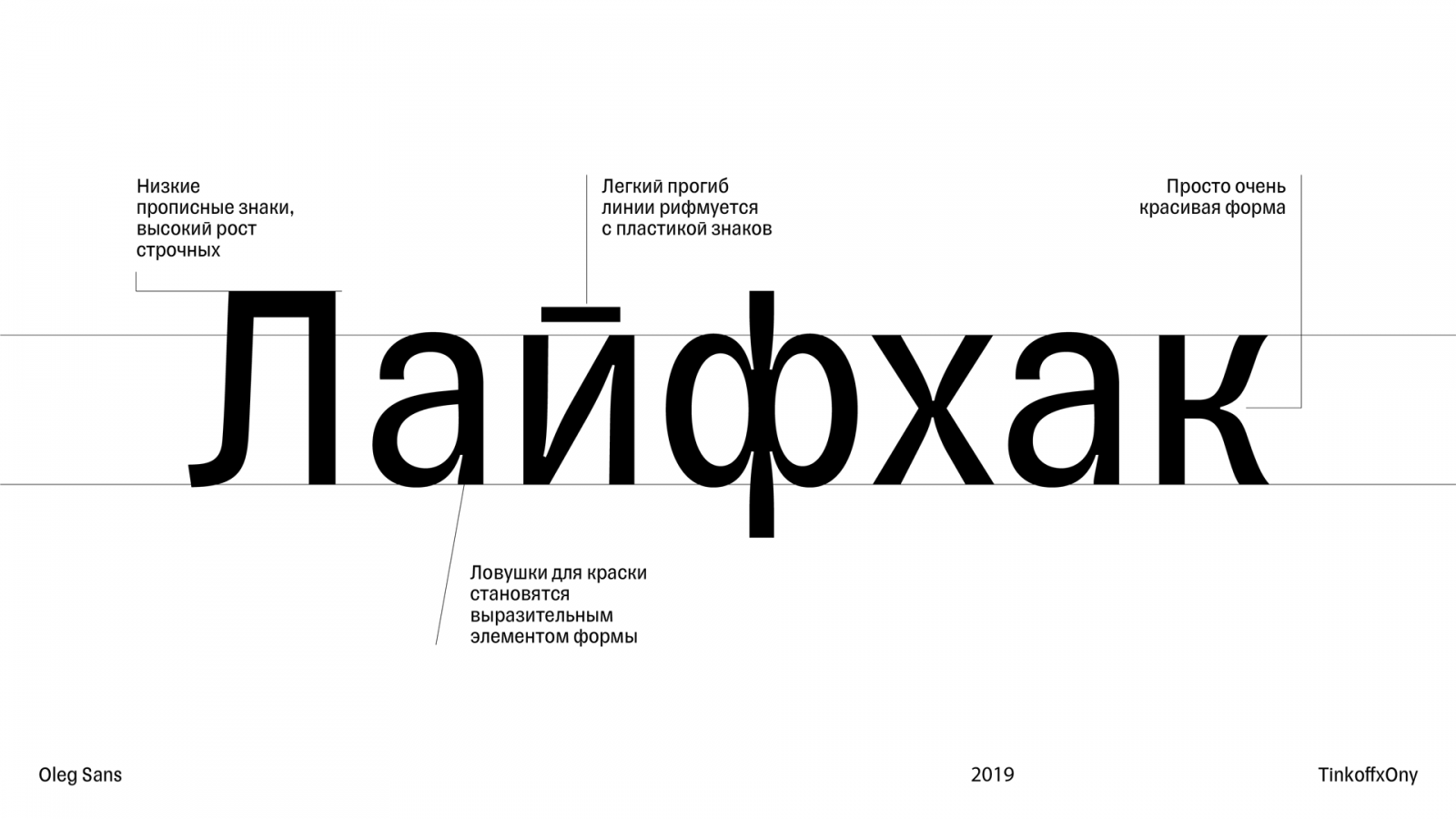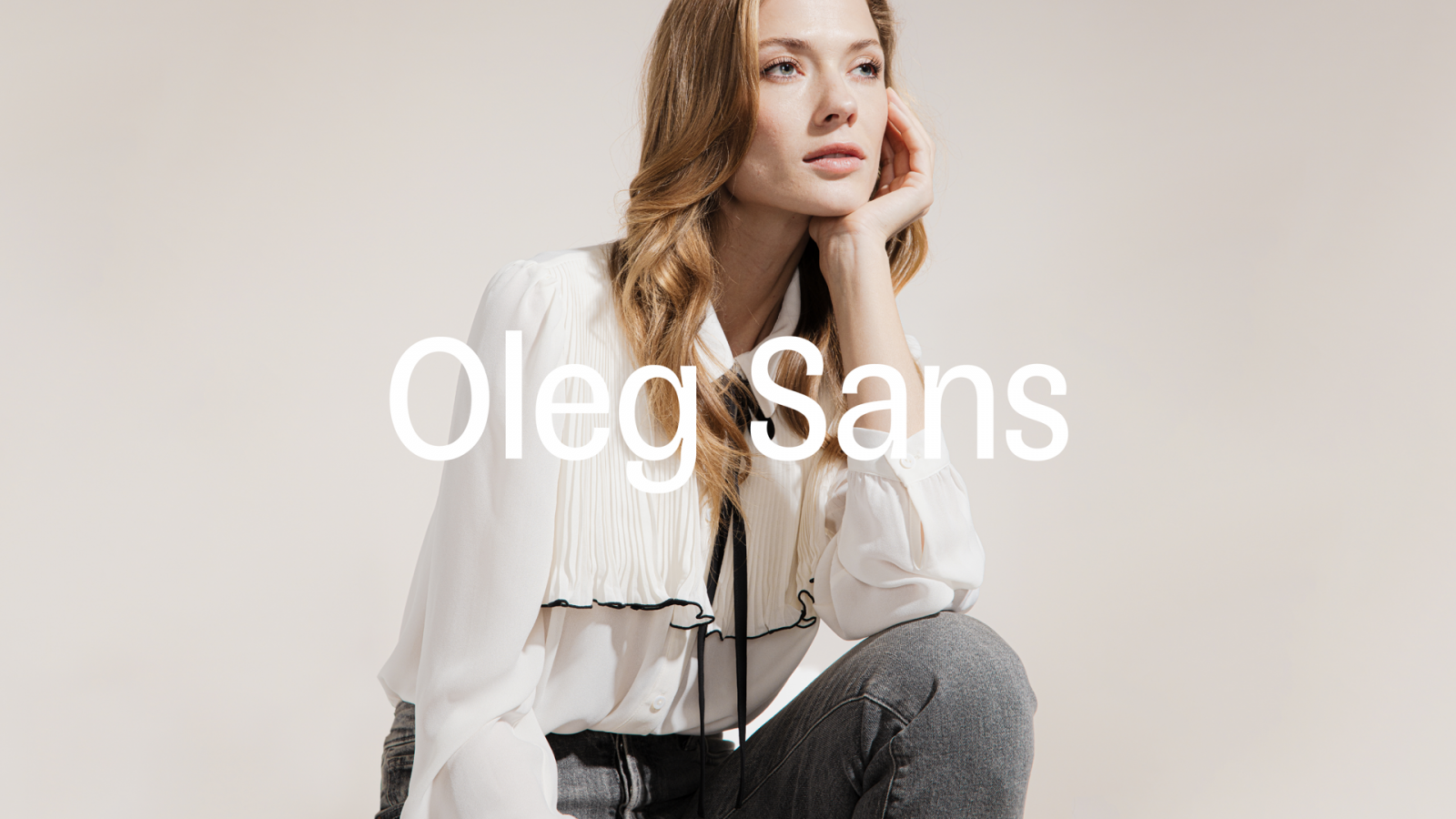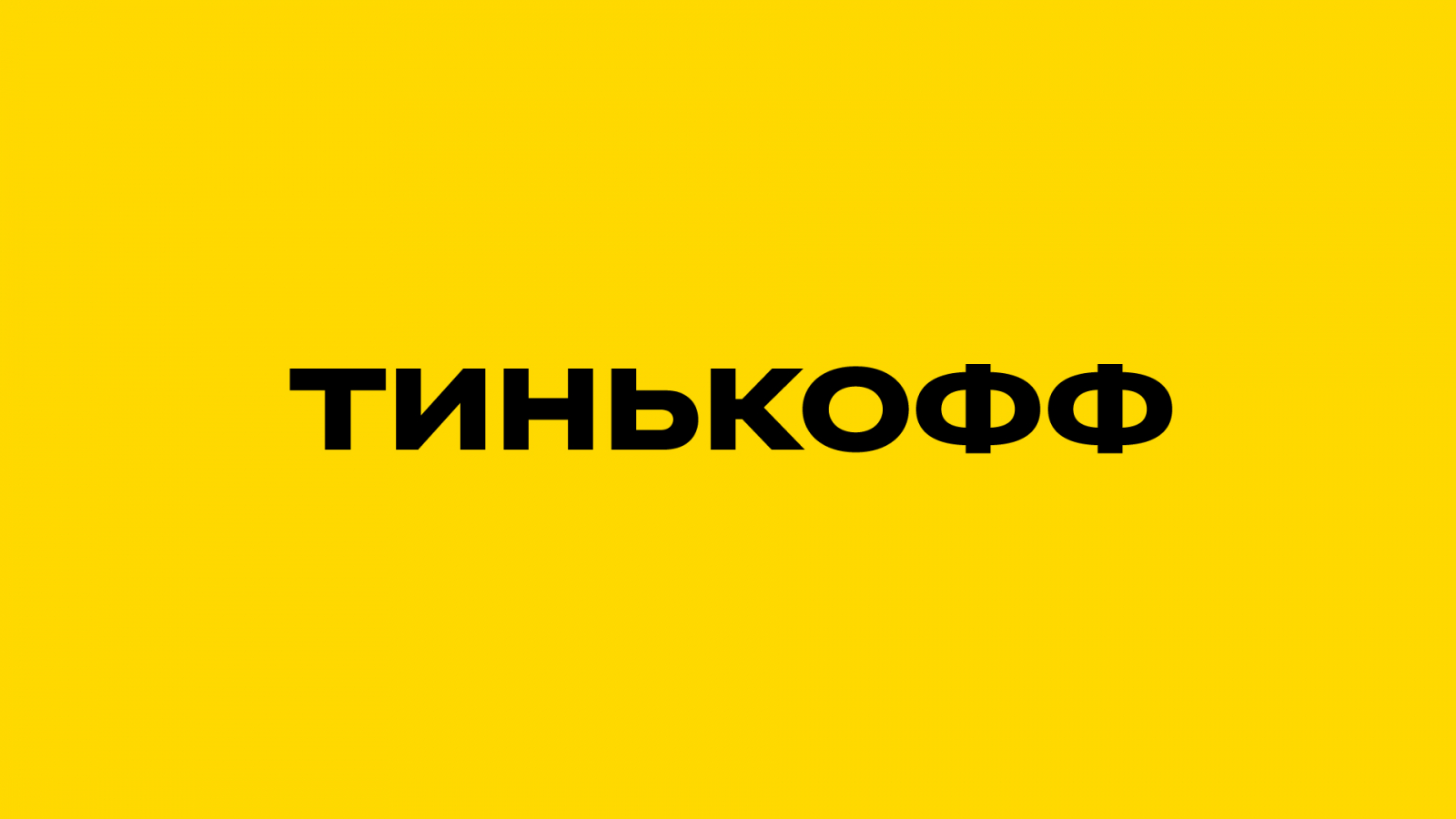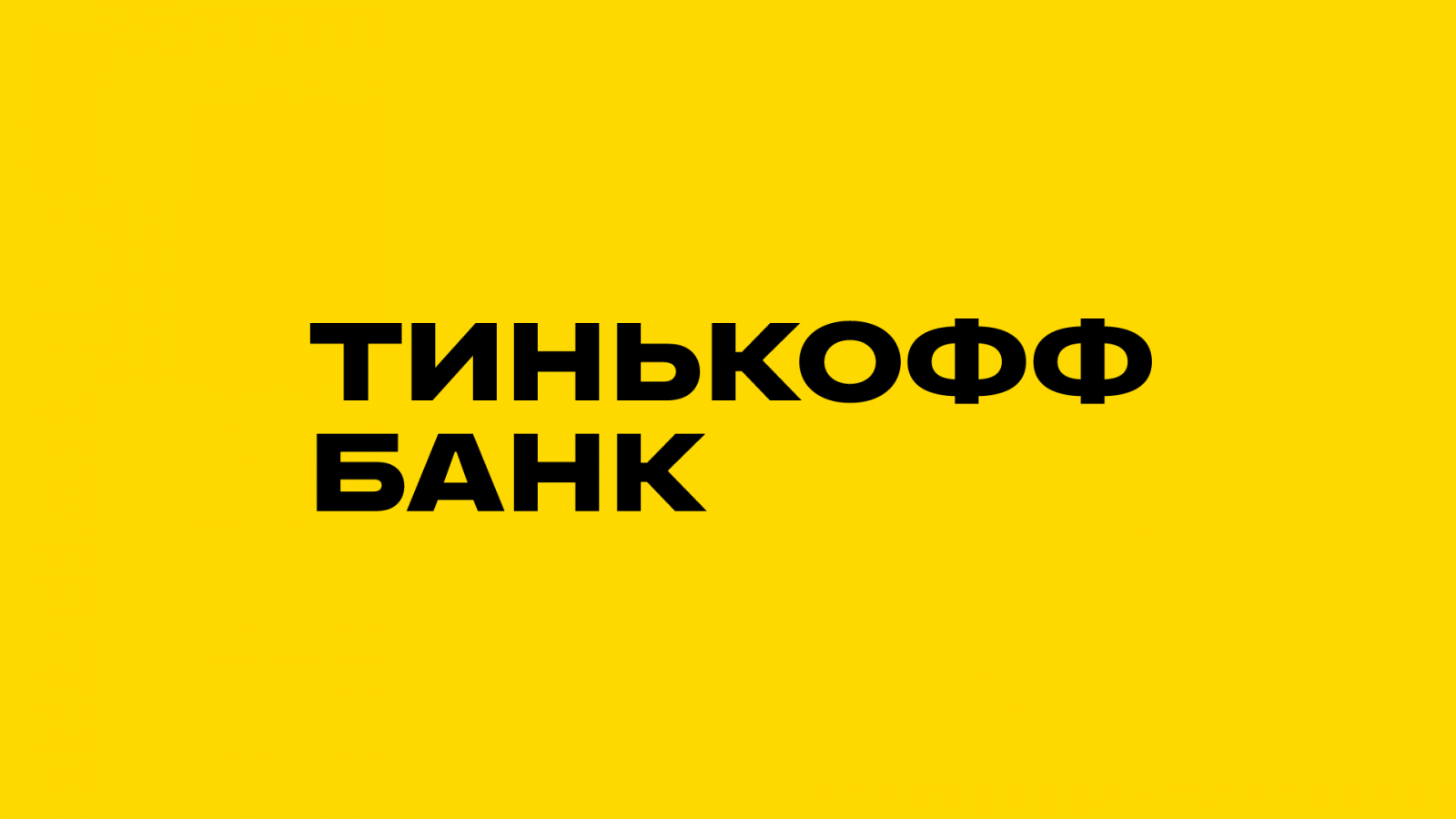
Агентство ONY разработало обновление фирменного стиля для «Тинькофф» — одной из крупнейших финансовых и лайфстайл-экосистем в стране. Глобальной задачей агентства было привести в порядок всю текущую дизайн-систему на уровне структуры и айдентики бренда, разработав понятный набор инструментов для контроля над единством и иерархией всех услуг и сервисов «Тинькофф».
В рамках обновления стиля стратегически важным стало решение закрепить «Тинькофф» как материнский бренд, стоящий над всеми сервисами компании, и использовать кириллическое написание бренда и продуктов во всех случаях, где это подходит по смыслу.
В поиске визуальной концепции агентство работало с существующими константами: фирменным желтым цветом и гербом, главным символом «Тинькофф».
Сергей Лавриненко, креативный директор ONY:
Первым шагом мы разложили герб на графические составляющие — два базовых цвета и черный контур. Эти элементы мы использовали для создания визуальной системы — она построена на слоях, похожих на открытые окна в системе компьютера. Так получилась единая среда с разными объектами внутри, отражающая множественность продуктов компании. Рамка работает как дополнительный акцентный элемент в рекламных коммуникациях, с ее помощью можно выделять важные смысловые части макетов или разделять блоки информации.
В процессе работы над стилем ONY также разработало два новых шрифта, которые помогут «Тинькофф» отстроиться от конкурентов и начать разговаривать на собственном языке. Первый — шрифт, которым набирается название компании и всех ее сервисов: широкий, основательный и подчеркивающий уверенный характер продуктов «Тинькофф». Второй — нехарактерный для финансовой сферы гротеск. По словам дизайнеров, у него необычные зауженные пропорции, удобные для использования в кириллической среде.
Давид Исаханян, вице-президент «Тинькофф», директор по дизайну:
Вместе с ONY мы решили провести fine-tuning существующего стиля и освежить его, чтобы привести к единому виду дизайн всей нашей экосистемы и объединить наши многочисленные сервисы под одним материнским брендом «Тинькофф». В рамках нового визуального стиля нам будет проще и быстрее запускать новые продукты, которыми будет пополняться экосистема «Тинькофф».
Для рекламных коммуникаций «Тинькофф» креаторы также разработали концепцию фотостиля. Что может быть хуже фотографий «успешного успеха» с Shutterstock? Только если ваш продакшен выдаст то же самое.
Новый фотостиль бренда прост: люди не должны смотреть в камеру, замирая в напряженной позе с неестественной широкой улыбкой — они должны быть расслаблены и вести себя естественно. Теплый свет разрушает барьер «банк — значит уныние», а чистые и естественные фоны удобно использовать в диджитал-среде.
Чтобы у бренд-команды были собственные референсы, агентство провело фотосессию, в которой показало взаимодействие объектов реального мира с фирменными цветными блоками и рамками.